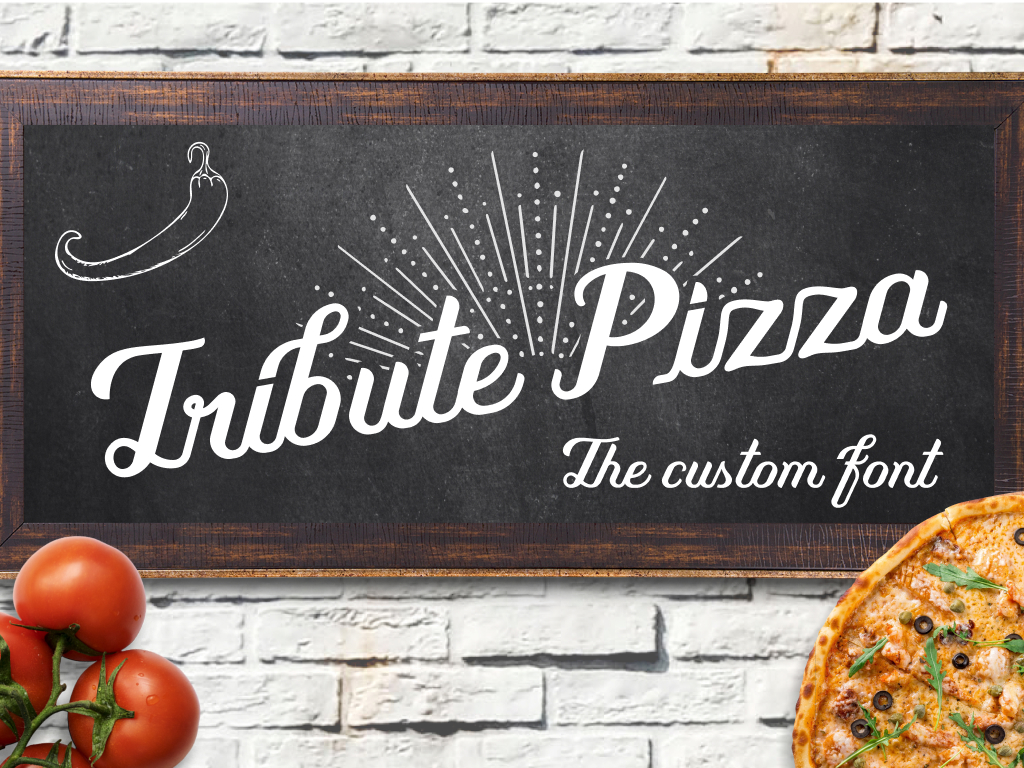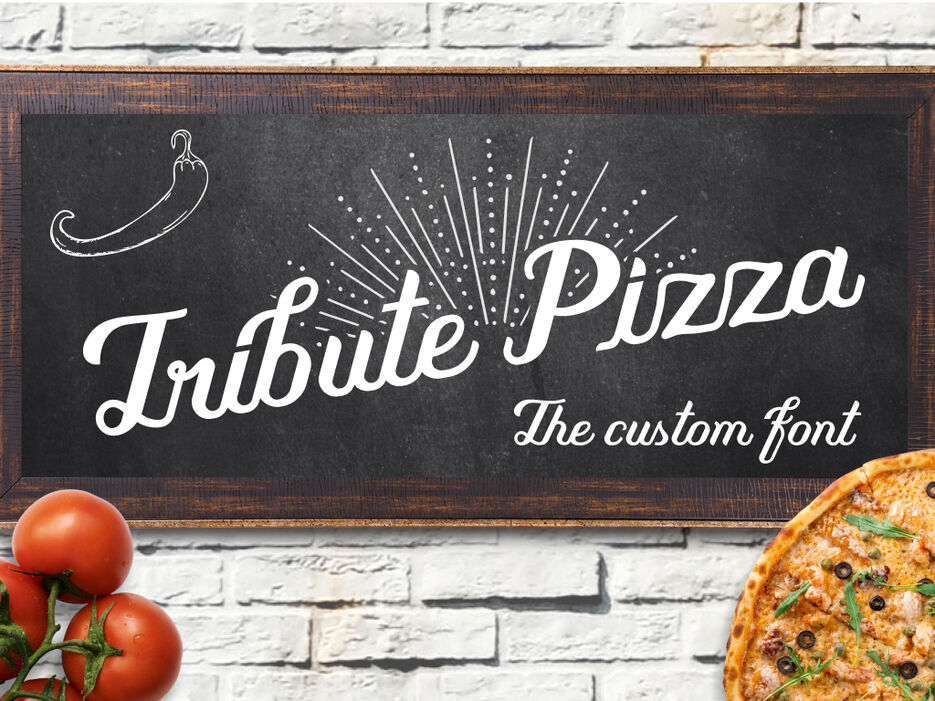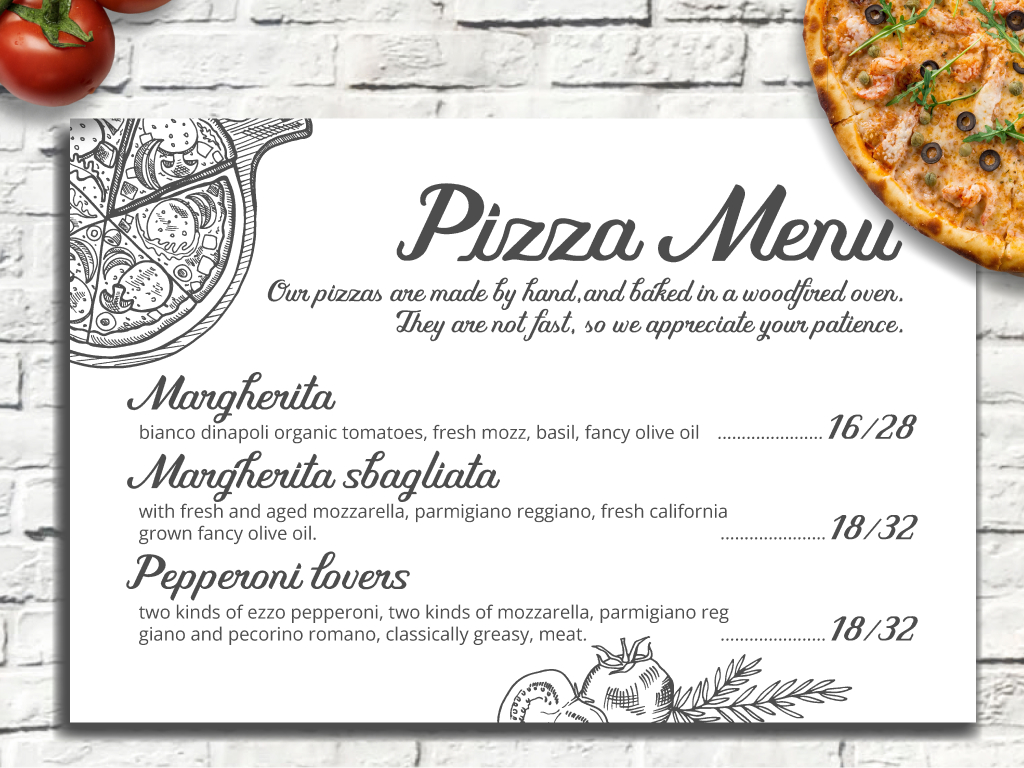
Tribute font
Tribute — шрифт, созданный в 2021 году на основе логотипа, разработан для клиента Upwork. Исходный леттеринг стал основой для создания шрифта.
Основной задачей проекта было превратить единичную надпись в шрифт, пригодный для дальнейшего использования. Нужно было сохранить его характер и ритм. В процессе были доработаны формы, выровнены пропорции и приведены к единому стилю все символы.